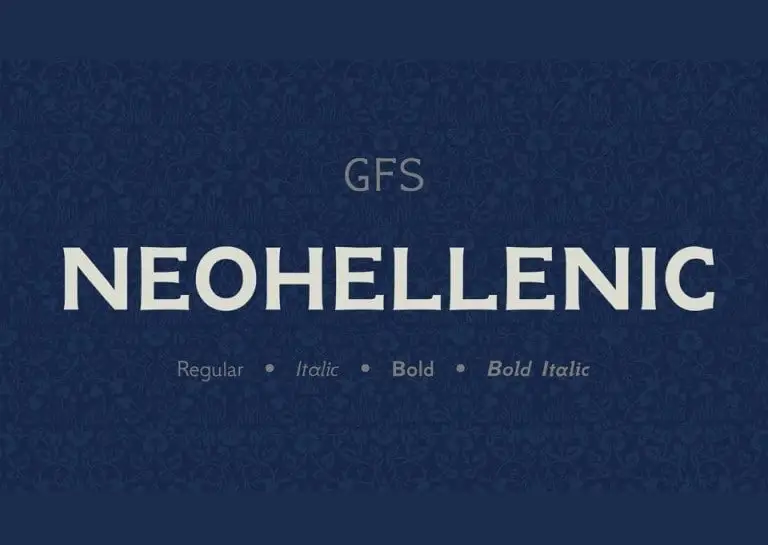
A NeoHellenic Serif Font é uma criação inspirada na famosa tipografia grega New Hellenic, desenvolvida pela Lanston Monotype Corporation em 1927 e projetada para homenagear a curadoria do British Museum Library pelo historiador Victor Scholderer. Essa fonte revivifica um tipo redondo e quase monoline que originou-se no livro de Macrobius, publicado em 1492 na imprensa do artesão Giovanni Rosso (Joannes Rubeus) em Veneza. Esta NeoHellenic Serif Font oferece um design clássico e elegante, perfeito para textos formais e atraente para anúncios de marcas. Sua inspiração na tipografia New Hellenic combina uma riqueza histórica com modernidade, resultando em uma fonte que é tanto uma homenagem ao passado quanto um legado do futuro da tipografia. Ideal para criações que buscam uma mistura sofisticada de clássico e contemporâneo, a NeoHellenic Serif Font está aqui para fornecer seu toque único a qualquer projeto gráfico ou design digitado.